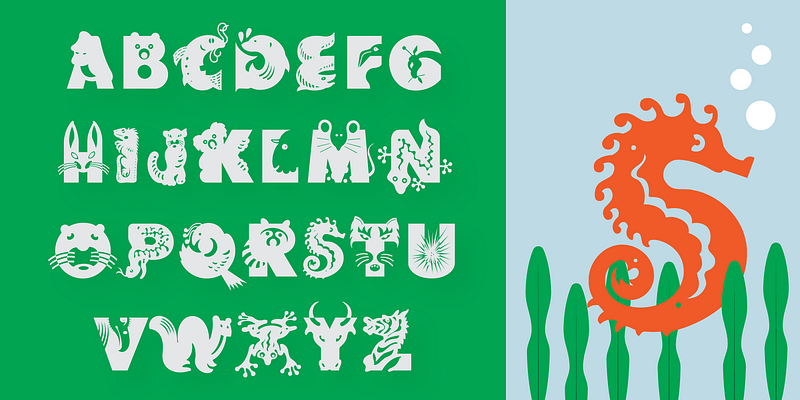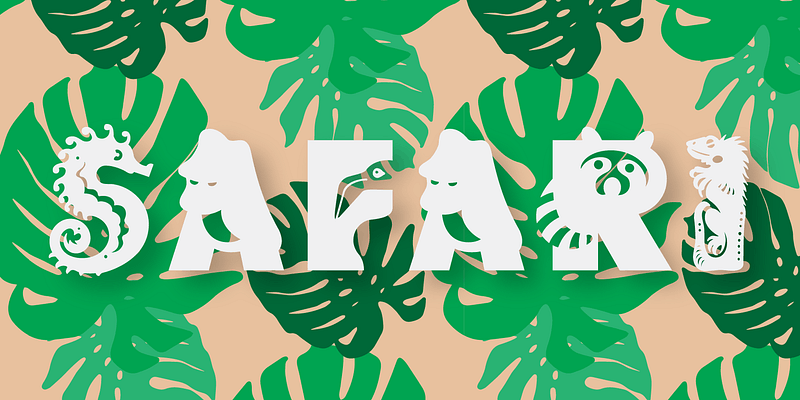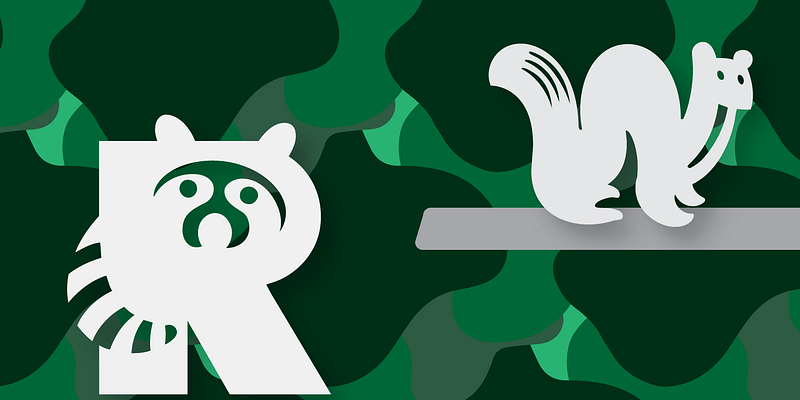
Ursprünglich von Craig Frazier, Designer und Illustrator aus San Francisco, für The Alphabet Critter Playbook entworfen, verraten Ihnen die cleveren Kreaturen von Critter ihren Namen anhand des Buchstabens, den sie repräsentieren. Ein hilfreicher Hinweis: „x“ steht für „Xenopus“.